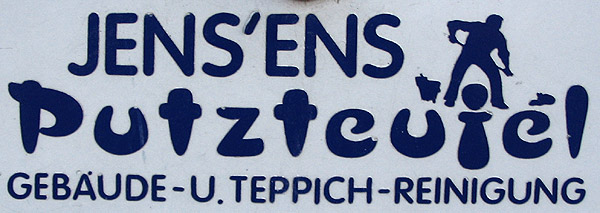
Momentan arbeite ich wieder an einem Fachbuch, diesmal zum Thema typografische Satzregeln. Frei nach dem Motto »aus Fehlern wird man klug« suche ich zur Illustration des Buches Bildmaterial von typografischen Fehlern aller Art.
Vom falschen Gebrauch von Anführungszeichen, Apostroph und Gedankenstrichen, bis hin zu sprachlichen Kuriositäten, sprich: alles, was beim heutigen Schriftsatz schief gehen kann.
Danke schon mal soweit für die Beiträge. Ich sollte vielleicht noch erwähnen: Neben solcher besonders »hässlicher Typo«, wie oben gezeigt, interessieren mich besonders die Satzfehler, die sich bei professionellen Grafikern, Journalisten etc. einschleichen.
Zum Bespiel sowas hier:
Da wird aus einem korrekten »Gute-Nacht-Bad« plötzlich ein freundlicher Gute-Nacht-Gruß ans eigene Bad ...
Oder Dreamworks, die ihren Film in Deutschland »Grosse Haie-Kleine Fische«, statt »Große Haie – Kleine Fische«. Gleich 3 Fehler in einem Titel. Keine Wunder, dass der Film floppte.
"Hier gibt's Gebrauchtwagen, "ANs" (das Autokennzeichen von Ansbach) und Verkäufe aller Art. Dann haben wir die - in diesem Fall völlig sinnlose - unterschiedliche Schreibung von Vor- und Nachnamen (Nachname versal), die Leerzeichen vor den Doppelpunkten, die uneinheitliche Handhabung bei der Benennung und bei der Gliederung der Telefonnummern, die überflüssige (und viel zu dicke) Unterstreichung der Handynummer, der unschöne Gedankenstrich in der Adresse, und die völlig falsche Straßenangabe (richtig wäre "Würzburger Landstraße"). Wer ganz genau hinsieht, erkennt zumindest auf dem Original, daß nicht nur die Autos links und rechts einfach gespiegelt wurden, sondern mit ihnen auch die Nummernschilder, d.h. diejenigen auf der linken Seite stehen jetzt in Spiegelschrift)."
Da kannst Du jeden Tag in die "Frankfurter Allgemeine" schauen. Die schreiben an der Stelle an der das lange s in der Texturschrift "Fette Gotisch" gesetzt werden müsste, das kurze Schluß- oder Silben s.
(lang s; vgl. Logo von Hasseröder, für alle die das lange s nicht kennen)
HALLO IHR leser über all in der internet und werbe welt ...
Nein, ich gedenke nicht, so wie in der Überschrift weiterzuschreiben (wobei ich, ganz nebenbei angemerkt, klar etwas anderes meine als "weiter zu schreiben", aber die Schlechtschreibdeform ist ein anderes Thema).
Aber die Werbebranche und die sogenannte "Internet Gemeinde" (wer auch immer das sein mag) tut das: alltäglich, allgegenwärtig und so penetrant, dass es echt weh tut! Wohl jede(-r) könnte hier stapelweise Beispiele bringen: jeder normale Prospekt überbordet an typographischen Peinlichkeiten, das Internet ist ganz offenkundig daraus hergestellt.
Ursachen?
1. Die "Internet Autoren" ...
Informatiker, also die Verursacher der allermeisten typographischen Fehler im Internet, sind (jedenfalls die allermeisten!) funktionale Analphabeten, für die klEin und gRoSs mehr oder minder bedeutungslos ist, die etwa nach,(!) jedem siebten Wort oder so etwa ein,(!) Komma setzen, statt Punkten am Satzende gewohnheitshalber ein Semikolon schreiben und in jeder Dialogsprache anglifiziert schreiben, also klein und auseinander. Das darf ich schreiben, weil ich es erlebt habe und ständig weiter miterlebe: als Informatik-Student (ach Gottchen, ist das lange her) hatte ich die lästige Pflicht, diverseste schriftliche Arbeiten anderer Informatikstudenten zu lesen. Manches wenige konnte ich lesen, Vieles musste korrigiert werden, Etliches habe ich mangels Lesbarkeit schlicht zurückgewiesen. Beispiele gefällig (aus meiner damaligen Kommilitonenschaft - wohlgemerkt: alle Autoren sind dem Ausweis nach Deutsche, in diesem Land geboren und aufgewachsen und haben irgendwie ein Abitur geschafft):
• Medezin
Elektotechnik
Veranstalltungen
... der Author zeigt das der Algorithmus den er hier benuzt schneller ist.
Außerdem kann sich jede(-r) selbst davon überzeugen: Wenn der Betreuer nicht selbst die Dialoge und Texte ediert, sind Foren oder Webmail-Interfaces in aller Regel grauenvolle Beispiele:
Webseiten (oder sollte man, der Gewohnheit folgend, nicht doch vielleicht"web seiten" schreiben? Bah!) selbst verweisen auf andere, ähnlich grotesk fehlerhafte Seiten natürlich auf der ...
Auch dieses Forum bietet im Datum ein unschönes Beispiel:
Den Verursacher solcher Magenkrampf-Texte, den typographischen Vergewaltigern der Sprache (leider nicht nur der deutschen, nur fällt's da besonder auf) fallen ihre Grausamkeiten eben gar nicht auf. Und die Einhaltung der (bzw. einer) Rechtschreibung steht nun mal nicht im Pflichtheft.
2. Die Werbebranche
Hier liegt die Sache - mit wenigen illustrativen Ausnahmen ...
... anders: nicht das schlichte Unvermögen sondern Absicht steckt hier in den ...
Aber: keine böse Absicht. Sondern schlicht die Absicht, den potentiellen Käufer zu erreichen.
Problem: immer mehr Menschen können längere Worte nicht mehr ohne größere Mühe lesen. Das liegt unter anderem an mangelnder Gewohnheit (statt Literatur wird, wenn überhaupt, Billigschund gelesen), aber natürlich auch am Mangel der Anforderung, es zu tun: man kommt ja gut ohne zurecht und braucht nicht mal für ein Germanistik-Studium ernsthafte Lese- und Schreibkenntnisse.
Mir haben schon einige Grafiker gesagt, dass die Regeln durchauchs zugunsten der Kreativität einfach mal außer Kraft gesetzt werden können ... sehen eben toll aus, so Zoll-Zeichen :?
Grundsätzlich stimmt das ja: Wer die Regeln versteht kann sie auch mal brechen.
Allerdings müsste es in diesem Fall schon *sehr* in den grafischen Bereich gehen, um einen Regelkenner dazu zu bewegen, die Regel bewusst und mit gutem Gewissen zu brechen.